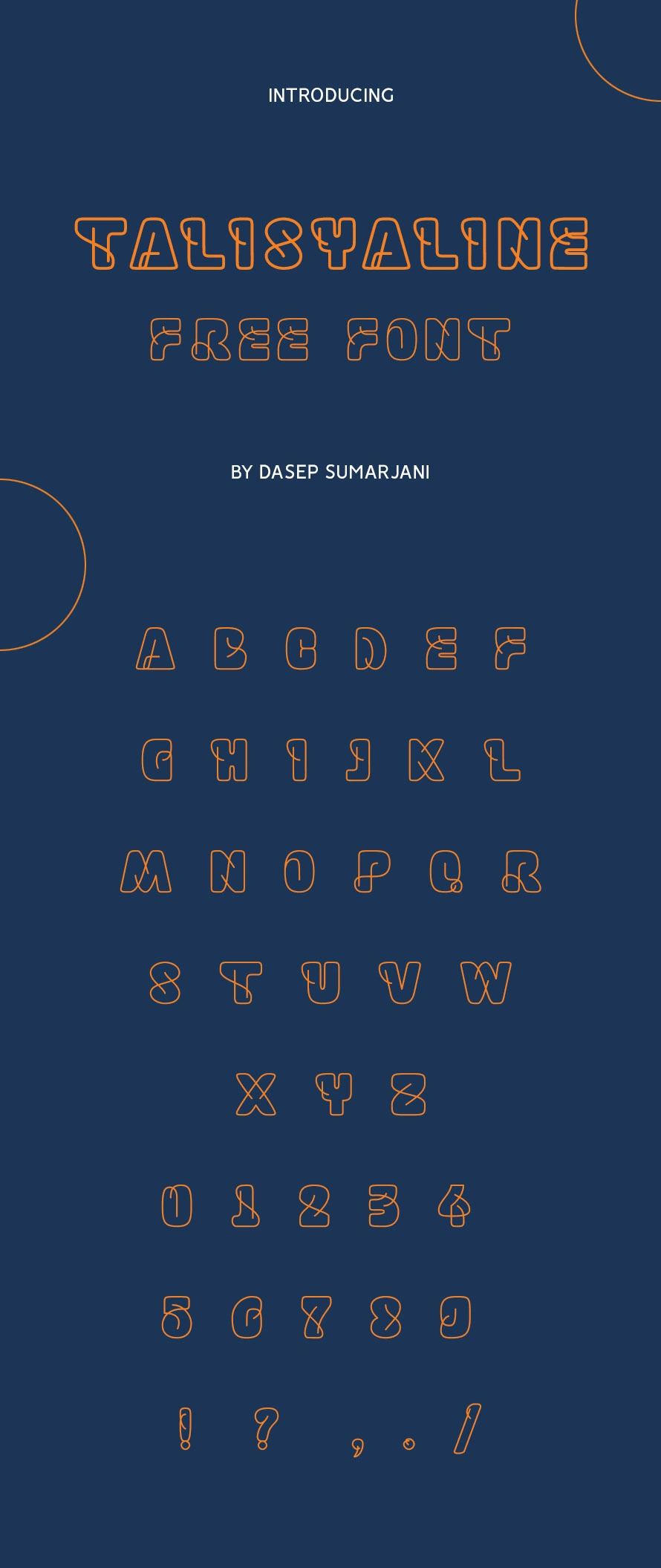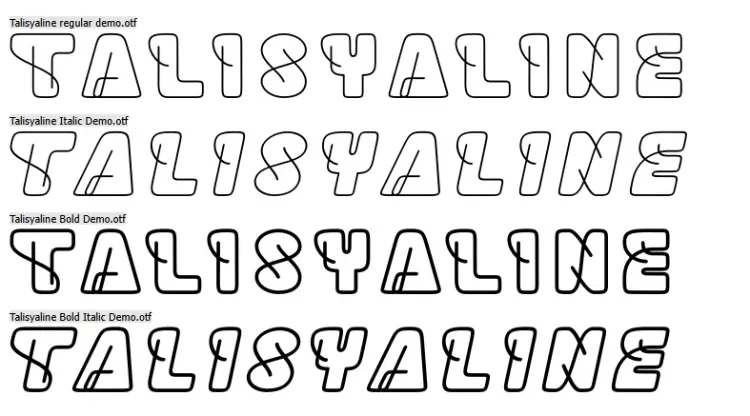
دانلود فونت انگلیسی Talisyaline
این فقط یک فونت توخالی معمولی نیست!
این فونت صرفاً یک طرح خطی برای حروف نیست، بلکه یک خط واحد است که در هر گلیف (کاراکتر) به دنبال یافتن فرم منحصربهفرد خود میگردد!
یک تایپفیس نمایشی برای پروژههای خاص
بهعنوان یک فونت نمایشی، TALISYALINE برای انواع پروژههای گرافیکی ایدهآل است، از جمله:
- لوگوهای خلاقانه
- جلد کتاب و مجله
- پوسترهای جذاب
- سربرگهای قدرتمند و بسیاری موارد دیگر.
ایجاد جلوهای مدرن و چشمنواز
با استفاده از فونت TALISYALINE، پروژههای شما بدون شک چشمگیرتر، قدرتمندتر، شیکتر و مدرنتر خواهند شد!